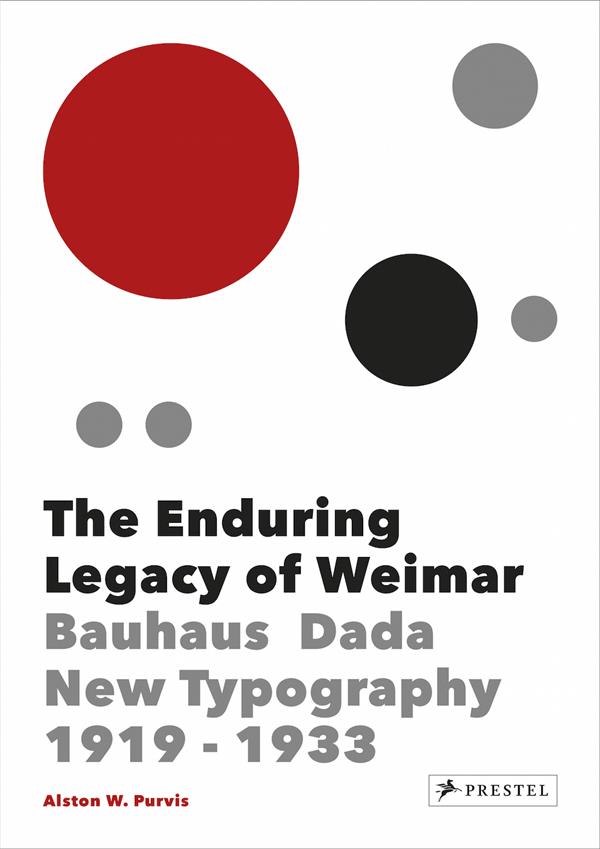
Livre neuf. The Enduring Legacy of Weimar. Graphic Design & New Typography 1919-1933. Cet ouvrage analyse la période comprise entre 1919 et 1933 et montre comment cinquante artistes ont su redéfinir le concept graphique, contribuant ainsi à la création et au développement du graphisme moderne en Allemagne. Dadaïstes, Futuristes et Constructivistes créent de brillantes innovations dans la typographie et le langage visuel. Sont présentés les travaux d'artistes tels que El Lissitzky, Jan Tschichold, Laszlo Moholy-Nagy, John Heartfield, Alexander Rodchenko...